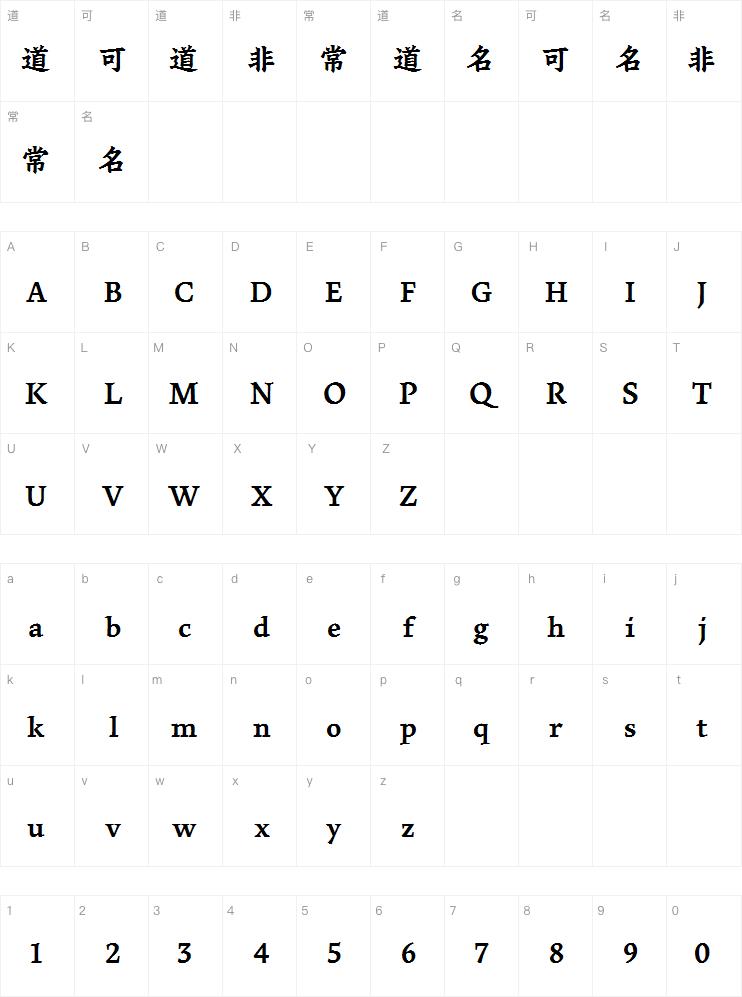
汉仪国图创新山海经75繁是一款充满古典韵味的字体,其设计灵感来源于中国古代的山海经。这款字体的特点是笔画粗重,线条流畅,有一种古朴而庄重的感觉。它的每一个笔画都充满了力量,仿佛在诉说着古代的故事。这款字体的线条处理得非常细腻,每一笔每一划都充满了设计师的匠心独运。它的线条既有力度又不失优雅,给人一种独特的视觉享受。